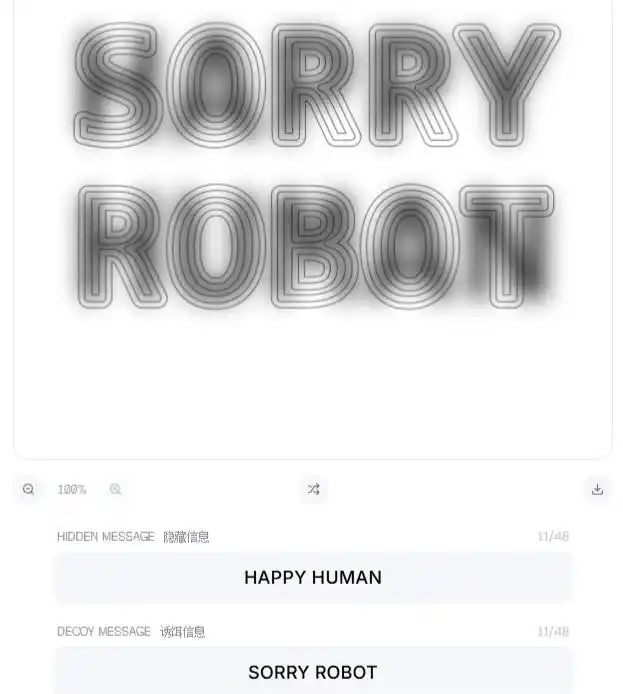
IT之家消息,Mixfont 于 7 月 15 日发布博文,宣布推出 TTF 格式的 Decoy Font 字体,通过叠加 2 层不同空间频率信息,让 AI 无法正确读取文字。
Decoy Font 字体基于混合图像(hybrid images)技术构建,该技术其中最著名的例子,是将阿尔伯特 · 爱因斯坦和玛丽莲 · 梦露的图像混合在一起。Decoy Font 基于相同理念打造,主要防止用户的文字内容被 AI 爬取。
Mixfont 称,多数 AI 系统读取图像文本时,主要依赖近距离像素信息,因此在输入图像进入大语言模型后,模型更容易优先读取轮廓更清晰的前景文字;而人在稍远距离观察时,更容易识别实际隐藏信息。
该公司工程师 Eric Lu 表示,每个真实的字母都隐藏在一个诱饵字母后面,这样 AI 就很难读出真正的消息。IT之家附上相关截图如下: